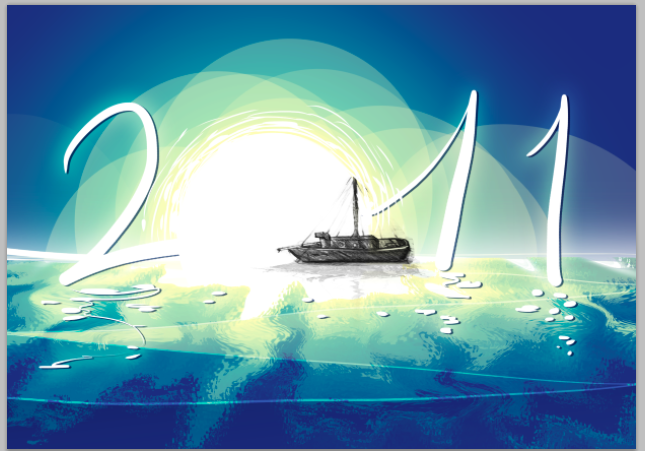
งานของนานา
:25: นานาชักเหมือนป๋าเลย์ทุกวันแระ ทำอะไรออกมาก็ดูดีไปหมด  :53:
ชอบงานเวคเตอร์  :25:
เอาล่ะ คือปกตินานาไปเรียนวาดรูปที่เมือง Ancenis ทุกวันพุธใช่ม้า
ละเหมือนว่าที่คลาสเรียนอาจารย์เค้ามีงานเข้ามา
เรื่องของเรื่องคือที่ Mairie (Town Council) ของเมืองที่ไปเรียน
เค้าอยากได้การ์ดเชิญไปงานอะไรสักอย่างที่จะจัดขึ้นตามเมืองลุ่มแม่น้ำลัวร์
เมือง Ancenis ก็เหมือนกัน เลยติดต่อมาที่อาจารย์ที่คลาส
ซึ่งอาทิตย์ก่อนแกก็พาเด็กๆทุกชั้นไปสเก็ตรูปแลนด์มาร์คและสิ่งที่เป็นสัญลักษณ์ของเมือง
อารมณ์ว่าจะเอามาทำงานคอลลาจ
ส่วนอาทิตย์นี้เด็กชั้นโตห้องนานาได้โจทย์เป็นออกแบบการ์ดเชิญที่ว่า
โจทย์คือการ์ดเชิญที่แสดงถึงความเป็นแม่น้ำลัวร์กับเมือง
บังคับให้ออกแบบร่วมกับภาพวาดที่วาดกันอาทิตย์ที่แล้ว
ค่อนข้างยากสำหรับเราเพราะเราเป็นคนคิดมาก  :30: อีกอย่างไม่ค่อยอินกับเมืองเท่าไหร่
ไอเดียสเกตๆของคนในชั้น  โดนชี้นำมาว่าให้เอา 2011 ใหญ่ๆ
เสร็จแล้วก็เหลือเอามาทำในคอม ทีนี้อาจารย์ถามว่าใครทำ ฟตช เป็นบ้าง
สรุปเลยมาลงที่เด็กกะเหรี่ยงนี่แหละ แต่อาสาทำนะว่างมากๆ :30:
หิ้วรีซอร์สกลับบ้านพร้อมหนังสือรีซอร์สภาพประกอบสองเล่มสมุดหน้าเหลือง  :55:
ปัญหาคืองานที่ได้มาเป็นสเกตเส้นดินสอบนกระดาษเอสี่ที่ไม่ค่อยขาวเท่าไหร่
สแกนเนอร์ก็ไม่มี ถ่ายรูปออกมาแล้วนรกมากเวลาเอาเข้าคอมแล้วต้องมาทำต่อ  :3005:
เลยทำไอเดียตัวเองก่อน มีรูปที่ต้องไดคัทน้อยดี (อย่างน้อยเรือก็วาดมาชัด  :30: :30: :30: :30:)
เหลือเอาสะพานมาทำเลขสิบเอ็ด แต่ดูรีซอร์สแล้วหนักใจ  :05:
ตูว่าอาจารย์ต้องช็อคพอเห็นฝีมือฟตช.นานา :30:
ไม่ได้ทำงานกราฟฟิกนานละนะ งงๆตัวเองอยู่  :30:
คือตอนนี้รู้สึกว่าจะพยายามไม่ใช่รีซอร์สฟรีตามอินเตอร์เน็ต
เรื่องของเรื่องคือขี้เกียจขออนุญาต คือถึงจะฟรีแต่จิ๊กมาใช้แบบมักง่ายแบบเมื่อก่อนก็กลัวซวย  :30:
ยากเหมือนกันนะทำทุกอย่างมาจากศูนย์เนี่ย  แต่พอทำได้ละก็แบบ เออ ก็ทำได้เนอะ  :47:
ประเด็นคืองานแบบโมเดิ้นๆเนี่ยแหละ ดูรีซอสแล้วแบบไม่ใช่แนวที่ชอบเลยอะ (จงนึกถึงคลิปอาร์ตในเวิร์ด)
ถ้าเป็นพี่นะ
- อยากทำรูปสะพานก็ออกไปถ่ายรูปสะพานเลย  :42:
- แล้วค่อยกลับมานั่งวาด/นั่งตัดต่อ จะได้ไม่มีปัญหา (ตูละเมิดของตูเอง ฟ้องไปเงินก็เข้าตัวตูเอง)
ป.ล. ลายเส้นกับโพสต์โปรดักชั่นต่างกันฟ้ากะเหว อยากทำได้อย่างนี้มั่ง  :07:
ทำงั้นไม่ได้อะ โจทย์บังคับคือคอนลาจจากลายเส้นที่เด็กวาด   :3005:
แล้วสะพานแต่ละอัน  :3005:
ทำเสร็จเซ็ทนี้จะกลายเป็นพวกลูฟี่ที่พาวเวอร์อัพแล้ว  :30: :30:
ผมว่ามันไม่เข้ากันสักอย่างเลยนะ นานาใช้สื่อชนิดที่ไม่เข้ากันมารวมกัน
เส้นดินสอแบบนั้น มันอยู่คนละโลกกับแผ่นสีแข็งๆ
หรือเทคนิคโฟโต้ฉ็อปแบบนี้้เลย ผมว่าสเน่ห์ของรูปเขียนที่เบี้ยวๆแบบนี้
มันก็มีของมันนะ ถ้าต้องเอาอันนี้เป็นโจทย์เริ่มต้น ผมก็ว่านานายังตอบไม่ถูกนัก
แต่ระบบความคิดที่จะตอบน่ะถูกแล้วล่ะ ที่จะเอากราฟิกมาแก้ปัญหา
ถ้าเป็นผม ผมจะเอาเท็กซ์เจอร์กระดาษอุ่นๆมาเริ่มต้น ให้ความรู้สึกสะอาดๆอุ่นๆ
งดความแข็งทุกชนิด แล้วจัดไทโปน่ารักๆ วางกริดดีๆ แล้วสีน่ากินๆเบรคๆหน่อยเหมือนที่เคยทำก็น่ารักดีออก
ใส่สะพานได้แล้ว  :07:
เท่กเจ้อนี่ไม่ใช่ไร คือถ่ายรูปสะพานมาแล้วกระดาษมันดำขี้เกียจลบ  :30:
เดี๋ยวแก้นิดนึงมันหนักขวาไปหน่อย เรือก็โดด
โพสช้าเพราะออกไปเดินเล่นมา อย่างไกลแต่สวยมากกกกก :07:
มาที่ไอเดียชาวบ้านมั่ง   :30:
จากไอเดียซ้ายล่าง
แอบขี้โกงวาดสะพานใหม่ เพราะไม่มีมุมที่ต้องการ
นอกจากลายเส้นกับเท่กเจ้อที่ถ่ายรูปมาแล้วก็เพ้นเอาหมดเลย ถ้าได้แก้งานนี่ก็ลำบากกันไปข้าง  :37:
ตุ๊กแกดี บอกไม่ถูก เดี๋ยวทิ้งไว้ก่อนค่อยกลับมาดู  :37:
สีน่ารัก สดใส :25: